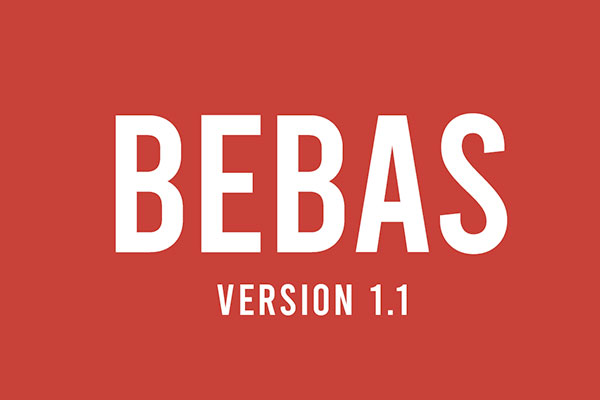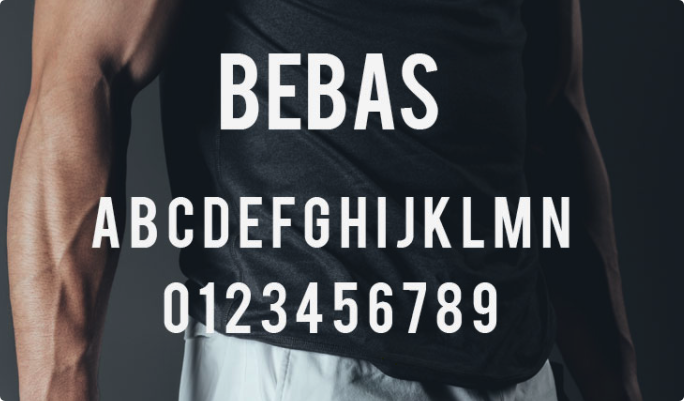
Bebas
Bebas是一款由国外设计师Ryoichi Tsunekawa创作的字体,其风格与著名的DIN字体相似。DIN字体以其优秀的外观和耐看性而广受欢迎,但遗憾的是,它是一款商业字体,使用时需要授权。而Bebas字体作为DIN字体的替代品,同样非常优秀,弥补了这一缺憾。
Bebas效果预览
Bebas字体效果预览